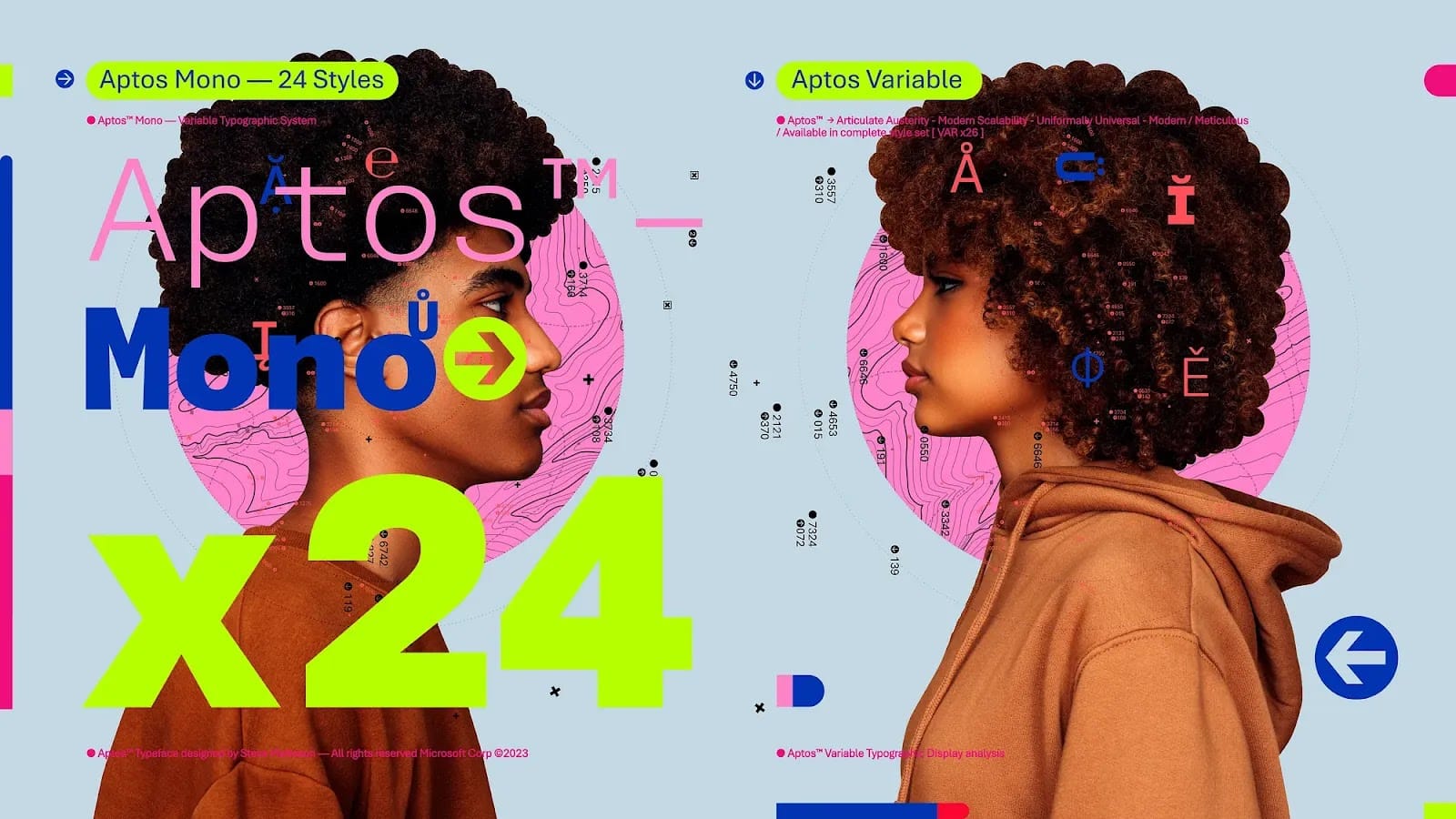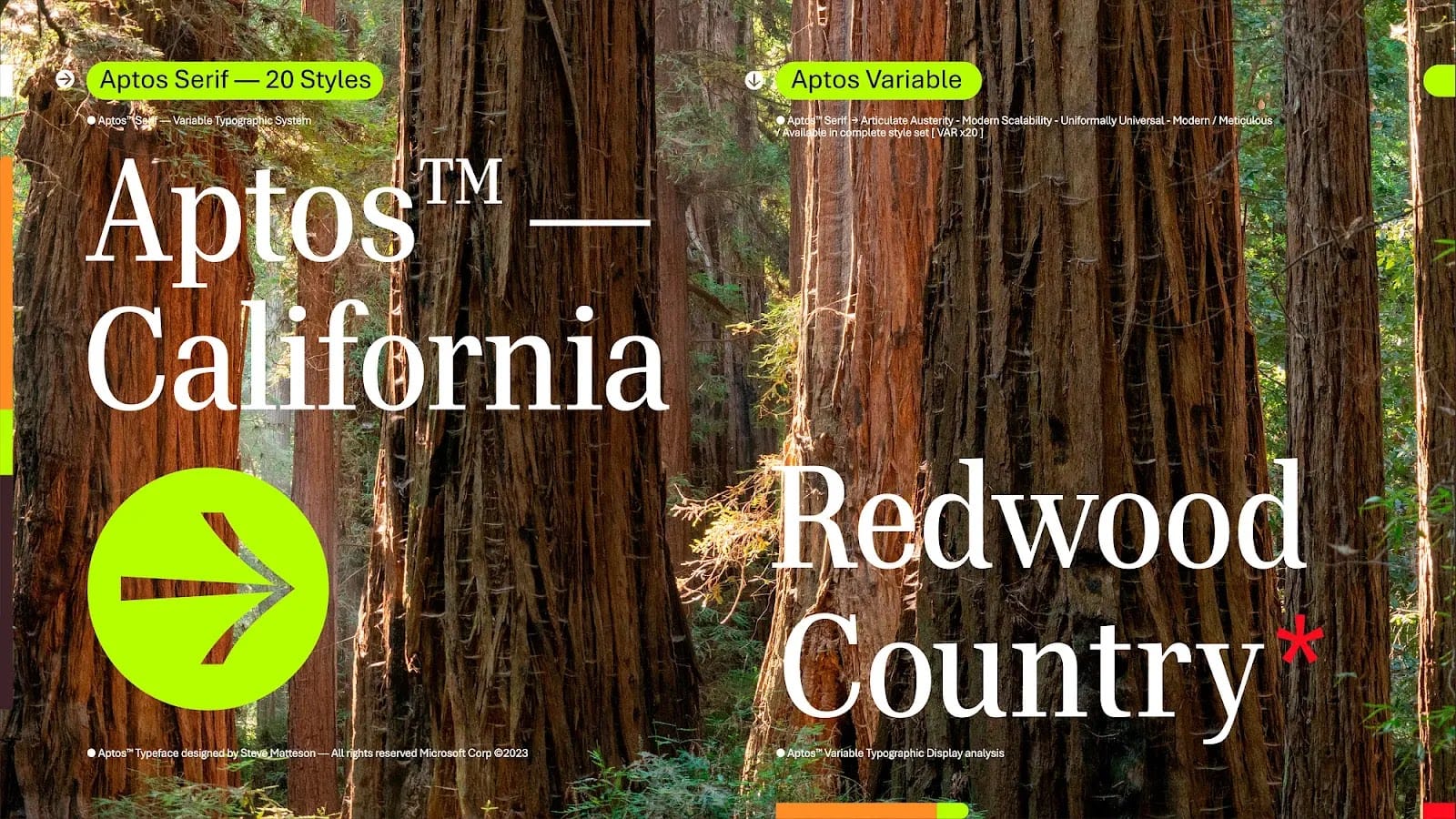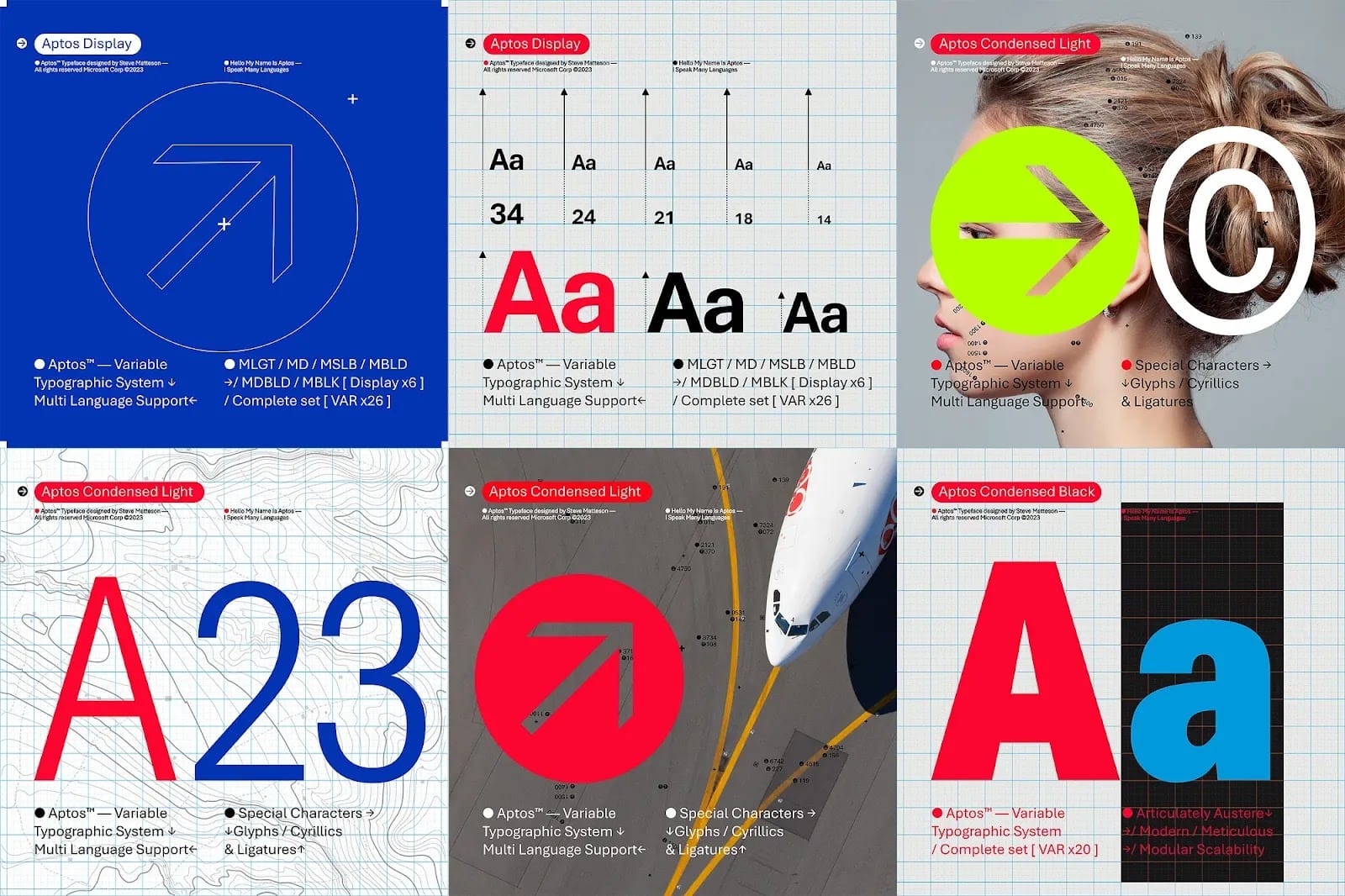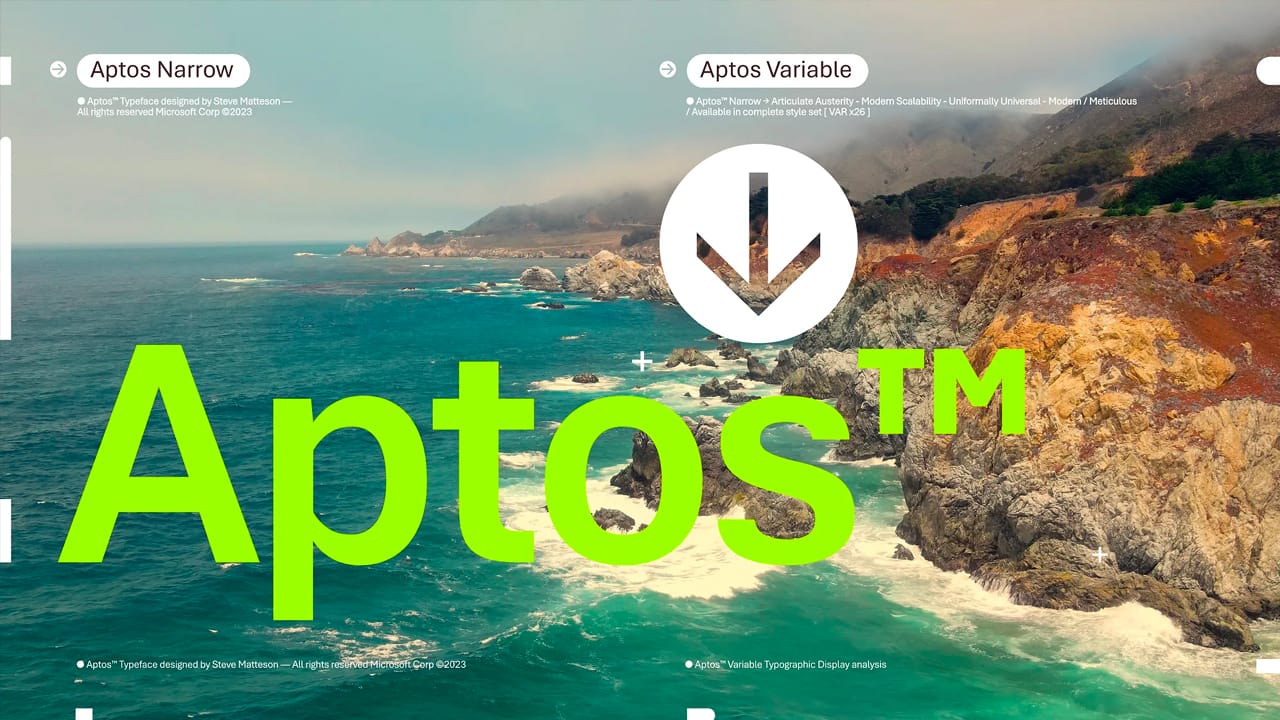
Calibri, phông chữ chính của Microsoft trong 15 năm qua đang dần bị thay thế bằng một bộ font mới Aptos, một kiểu chữ sans-serif mới lấy cảm hứng từ kiểu chữ Thụy Sĩ giữa thế kỷ 20. Trước đây được gọi là Bierstadt, Aptos là một phần trong nỗ lực tìm kiếm phông chữ mặc định mới của Microsoft trong vài năm qua. Gã khổng lồ phần mềm đã đặt hàng 5 phông chữ tùy chỉnh mới cho Office vào năm 2021 và phông chữ Aptos đã được chọn làm mặc định sau nhiều năm phản hồi từ người dùng.
Aptos được tạo ra bởi Steve Matteson, một nhà thiết kế kiểu chữ nổi tiếng. Trước đây ông đã tạo ra Segoe, được Microsoft cấp phép để sử dụng làm phông chữ mặc định của Windows. Microsoft lần đầu tiên bắt đầu sử dụng bộ phông chữ Segeo UI trong Windows Vista và ngày nay nó vẫn được sử dụng trong Windows 11. Bierstadt đã được đổi tên thành Aptos theo tên thị trấn nhỏ ở California, Mỹ.
Mặc dù Aptos sẽ thay thế Calibri mặc định, nhưng Calibri vẫn được ghim sẵn ở đầu menu phông chữ mới cùng với các phiên bản tiềm nhiệm của nó là Times New Roman và Arial. Calibri là phông chữ Office mặc định kể từ khi phát hành Office 2007, thay thế cho Times New Roman vào thời điểm đó.
Aptos được tạo thành từ các hình dạng hình học khác nhau, đậm nét, rõ ràng, có tính định hướng và ràng buộc. Nó thể hiển nhiều ngôn ngữ và tông màu khác nhau. Phần cuối của thân chữ được thiết kế gọn gàng. Các hình vuông tròn tinh tế trong đường viền của các chữ cái cho phép mức độ dễ đọc cao hơn, đặc biệt là ở các chữ có kích thước nhỏ.Giống như tất cả các phông chữ MS Office mặc định trước đây, Aptos hướng đến sự chuyên nghiệp, dễ thích ứng và tinh tế, như một kiểu chữ mặc định. Aptos hiện có sẵn trên Microsoft 365.